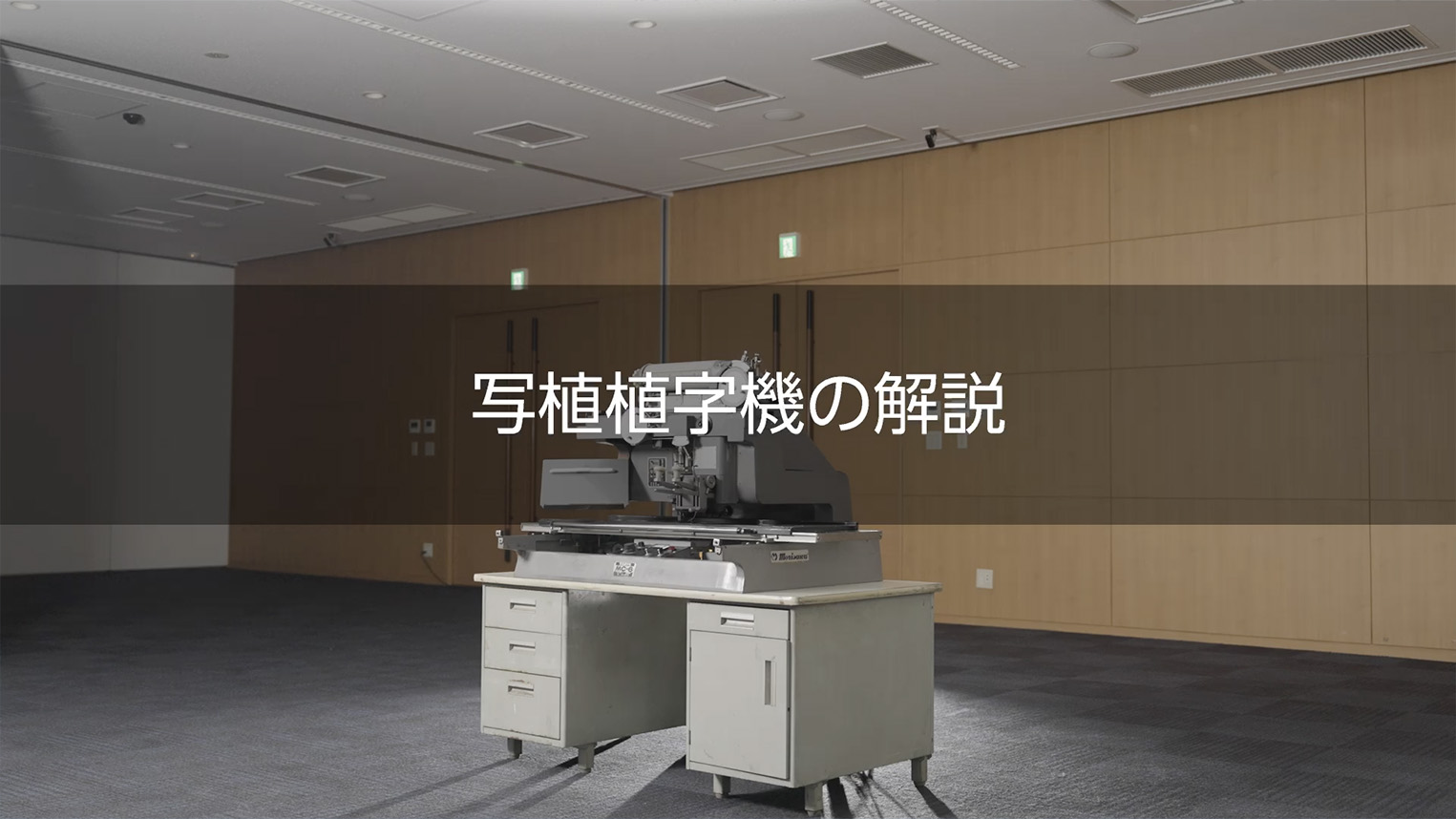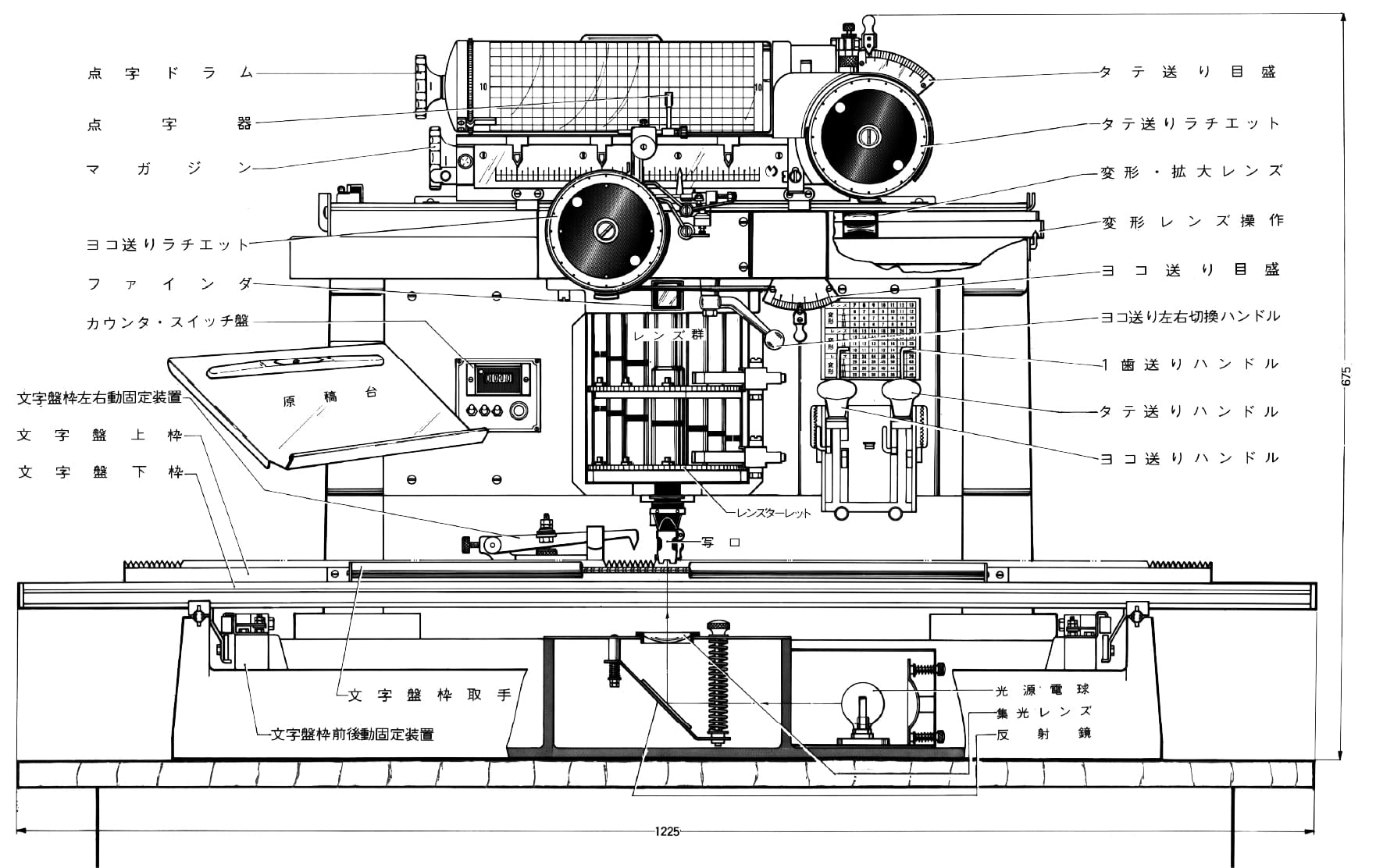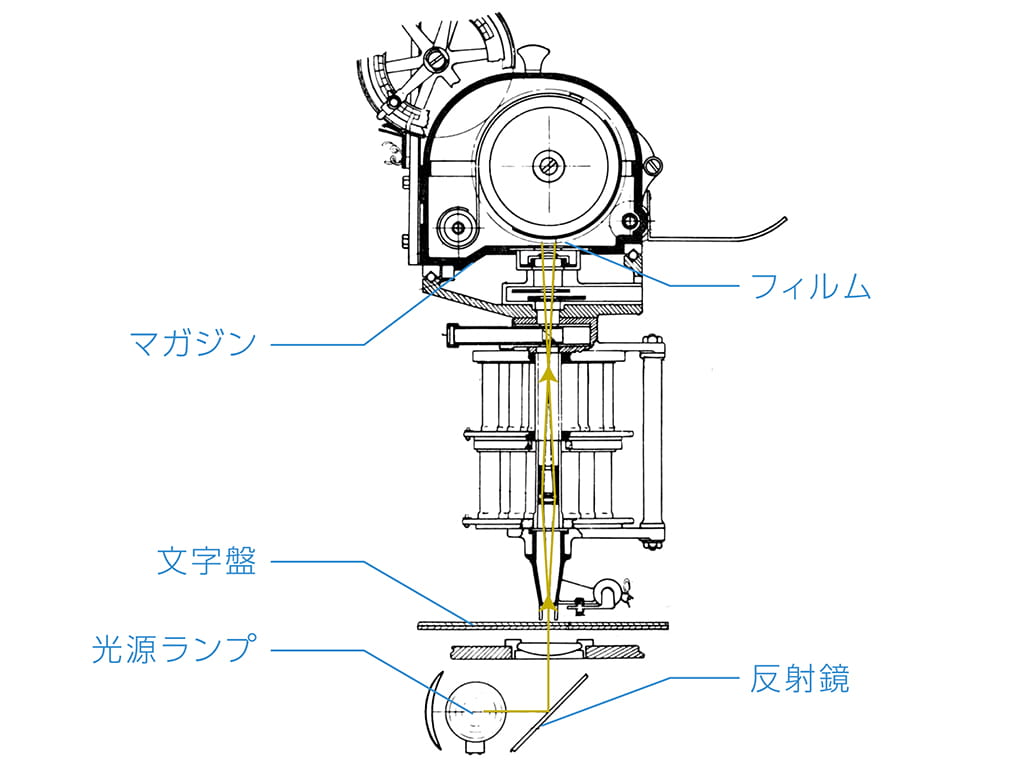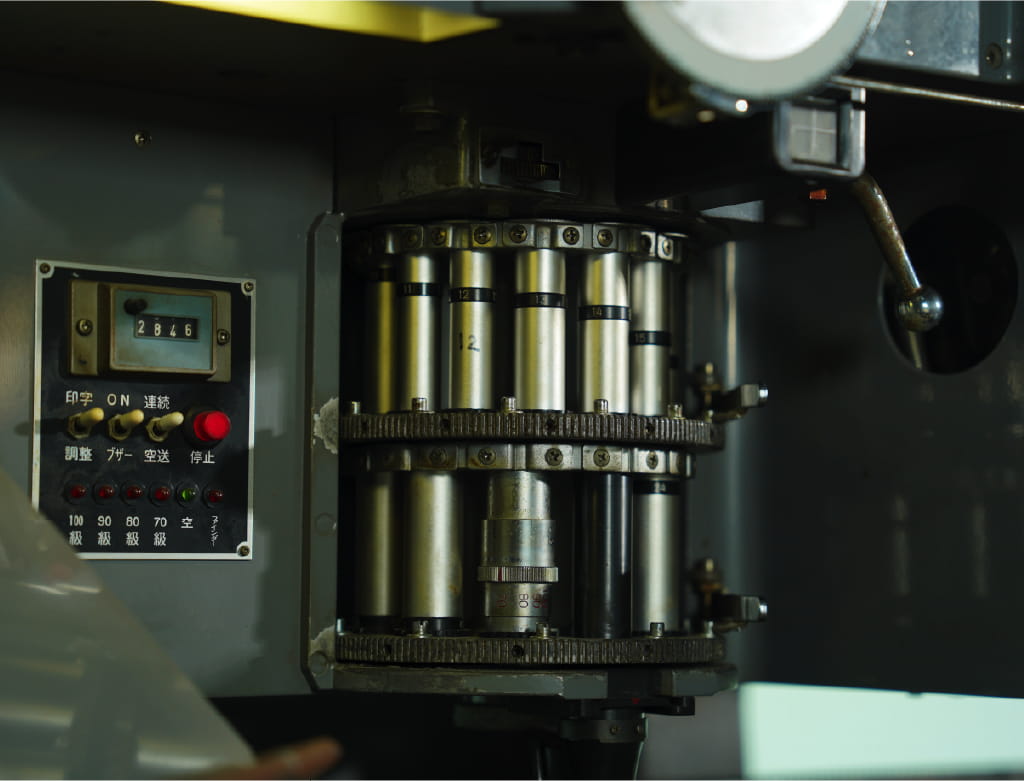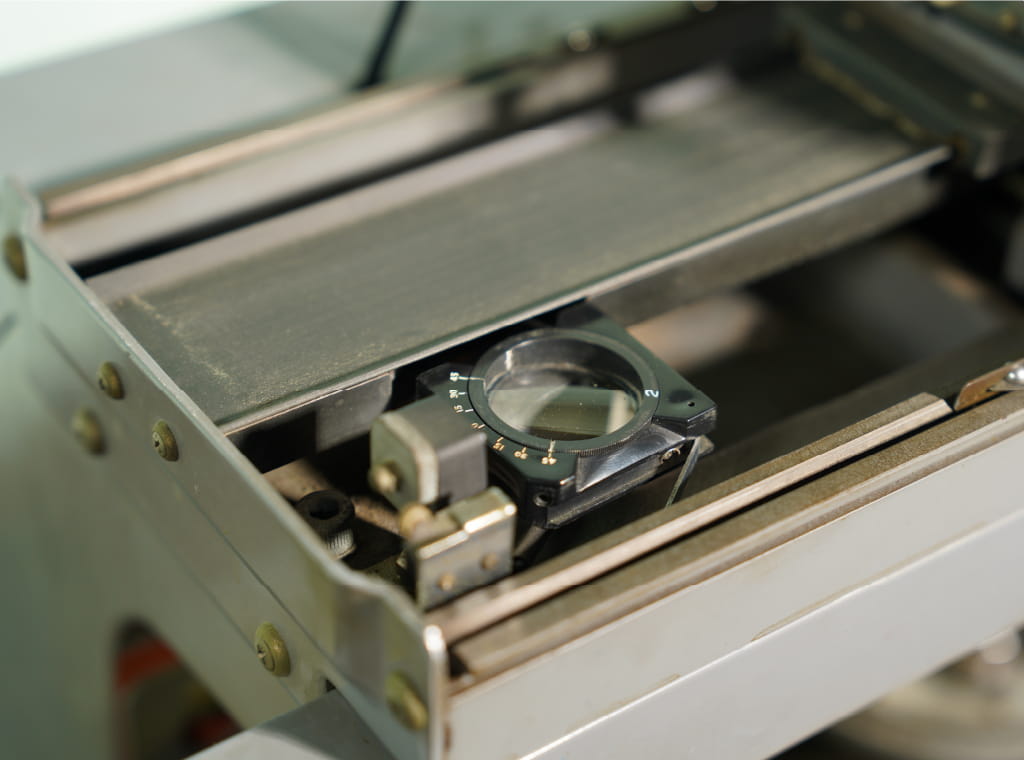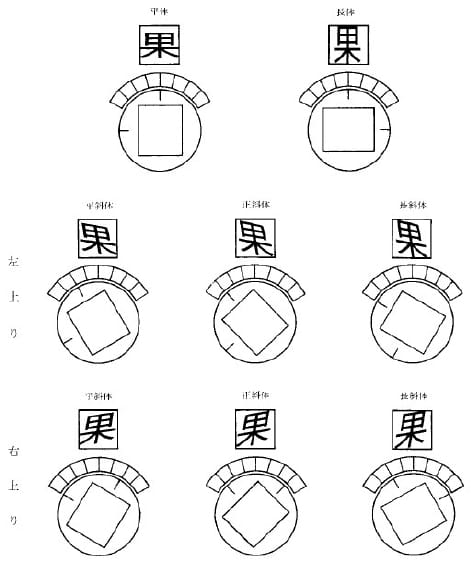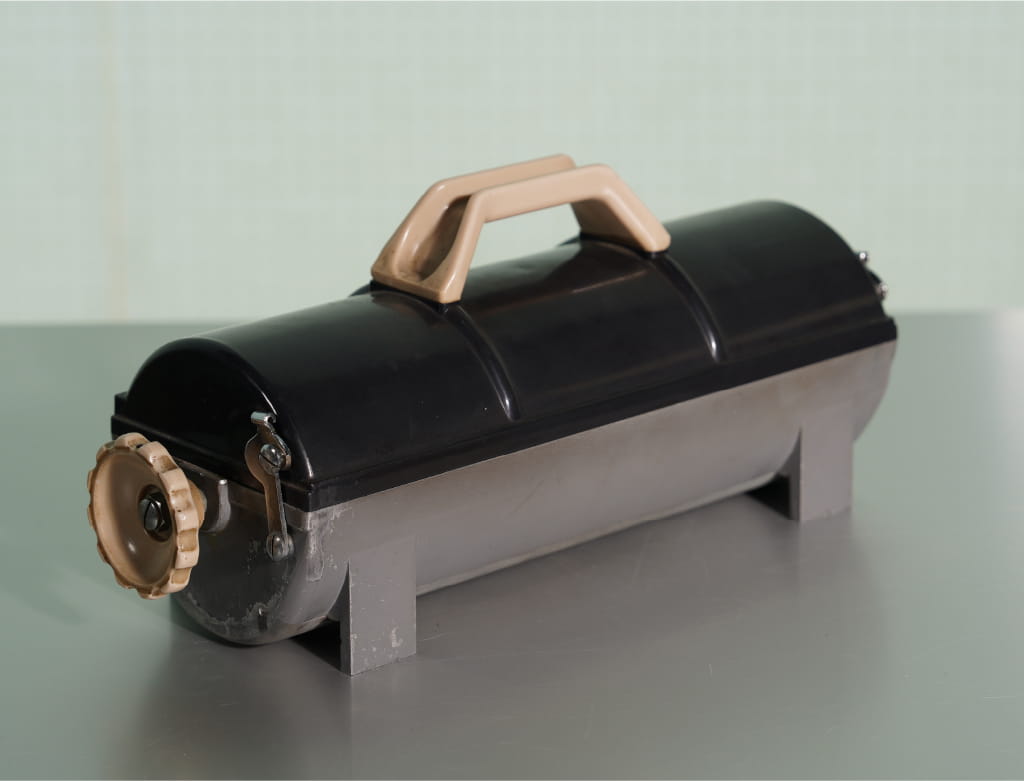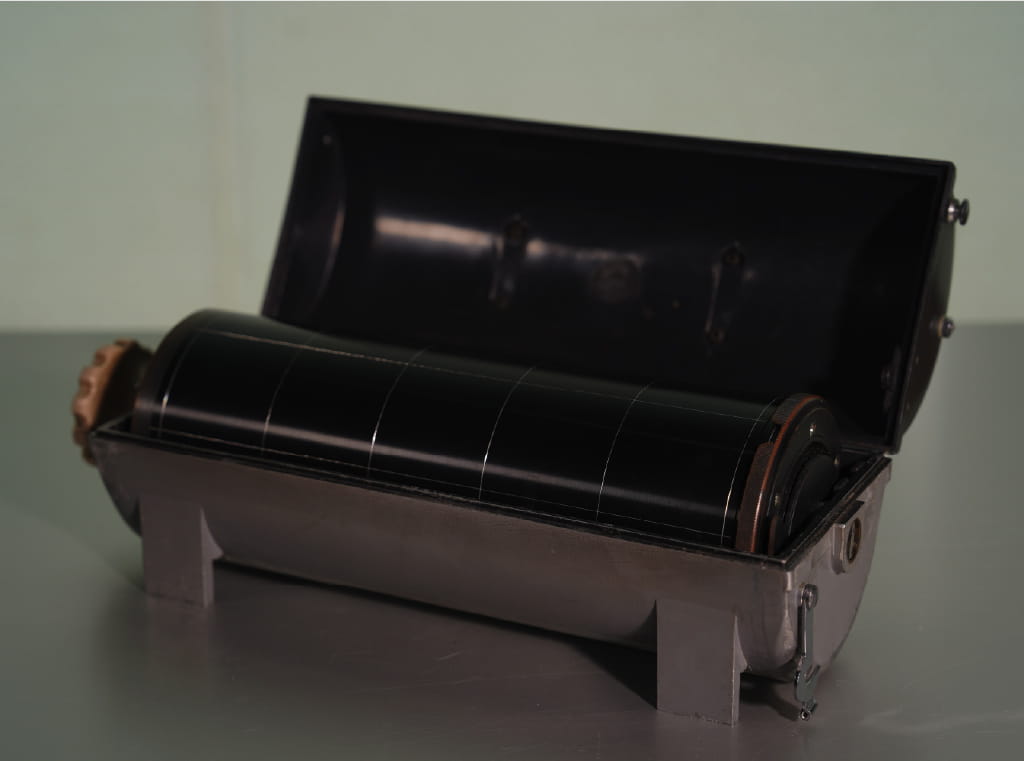
邦文写真植字機
1924年7月24日に弊社創業者森澤信夫が邦文写真植字機の特許を出願し、石井茂吉氏とともに研究・開発を進めた世界初の邦文写真植字機が世に知られることとなりました。
写真植字機の発明はその後の印刷工程に大きな変革を起こし、オフセット印刷の普及によりその活躍の場を確固たるものとし、またその自由度からデザインの広がりにもさまざまな場面で貢献することになりました。
ここでは写真植字機発明から現在のモリサワにいたる変遷や写真植字機の構造をご紹介します。
写真植字機は、従来の活版印刷に代わる新しい印刷技術を導入した装置です。その原理は、光学写真の技術を応用して文字を印字し、組版を行います。
従来の活版印刷では、大量の活字を用意し、それらを収納するための広いスペースが必要でした。しかし、写真植字機は光源からの光を文字盤に通し、それをレンズで拡大縮小し、最終的に印画紙やフィルムに焼き付ける方式のため、広いスペースを必要としないコンパクトで画期的な装置です。
2文字盤
文字を採字するうえで重要な文字盤の文字の配列は「一寸ノ巾(いっすんのはば)」とよばれる方式が採用されました。この配列は、すべての漢字を51の基本部首(大見出し)から、169 の部首(小見出し)へと分類され、合わせて220の部首に分類することで、漢字の読みが分からなくても目的の漢字を素早く見つけられるようにした便利な配列として支持されました。
3レンズ
レンズはマガジンから垂直におろされた円筒に装着されています。
主レンズ、拡大レンズ、変型レンズの三種が用意され、文字の大きさを決める主レンズは複数取り付けられるようになりました。
シャッターも耐久性が必要なため独自に設計されました。
かまぼこ板型レンズと呼ばれるかもぼこの断面に似た半円型レンズの角度を変えることによって文字を変型できます。「果」の文字を囲んでいる枠が仮想ボディです。
4マガジン(暗箱)
レンズを通ってきた光はマガジンの中にある印画紙に焼き付けられました。円筒形のドラムに印画紙(フィルム)を巻いて暗箱に収納します。印画紙の装填作業は暗室内で行われました。
マガジンが取り外しできるようになったのはMC-5型からです。従来までは、印画紙、フィルムなど感光物を着脱する際は、ドラム部分を黒布で遮光して行っていました。外部装填マガジンにより、その作業は暗室で行うことができました。また、複数のマガジンを用意して大量の印字物にも効率よく対応できるようになりました。
5ラチェット
植字(組版)するためには印字位置を移動させなければなりません。そのための機械的な駆動部分として、ラチェット(爪車=のこぎり歯状の歯車)を利用して、印字ごとに全角分印画紙を送るしくみがつくられました。
開発の段階においてメートル法を採用しており、字送りや行送りを示す「歯(=0.25mm)」という単位の名称はこのしくみから来ています。